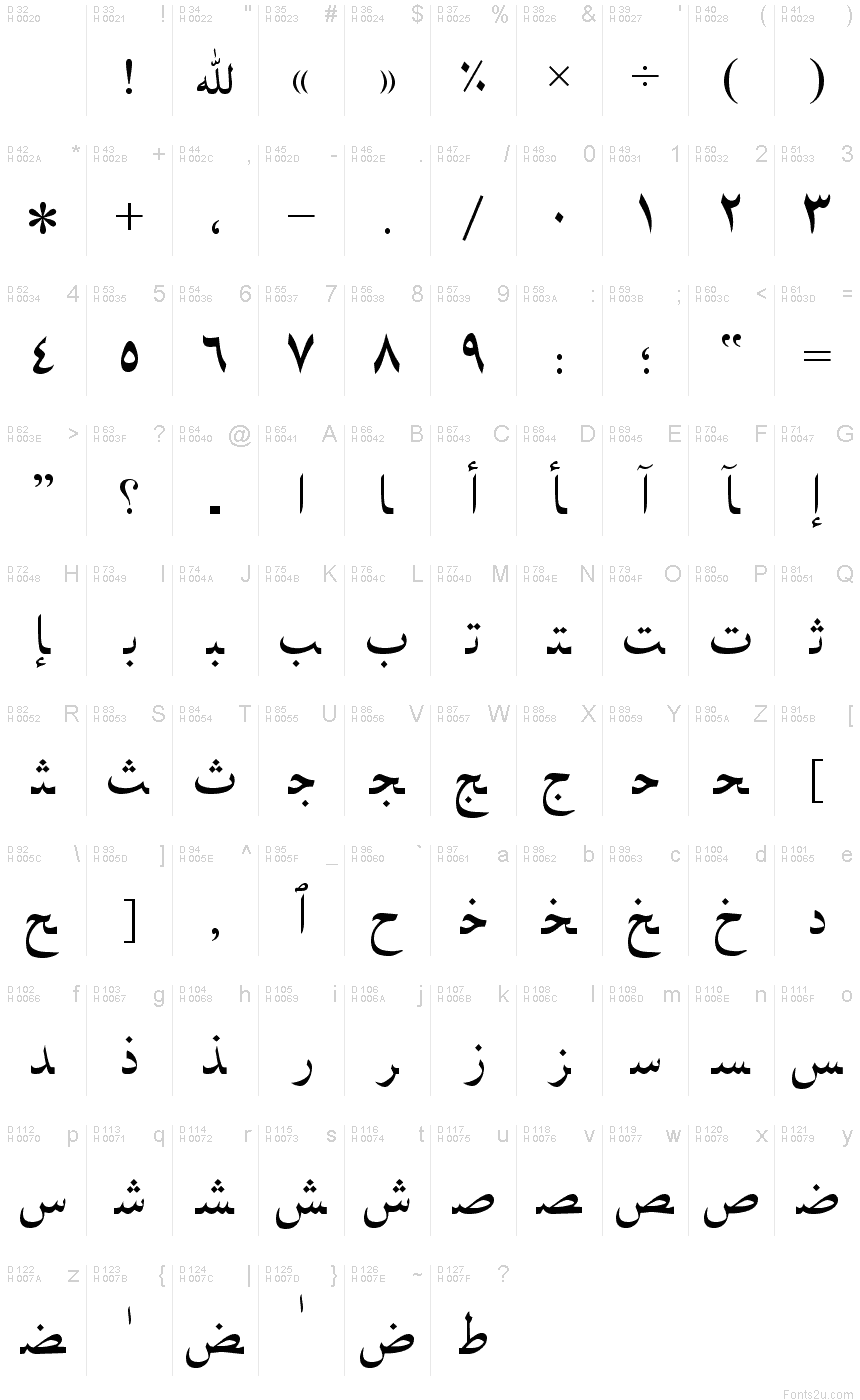
ArabicNaskhSSK
Arabic Naskh SSK, przypisywany Southern Software, to darmowy arabski krój pisma kaligraficznego z szerokimi, połączonymi pociągnięciami i ostro wyciętymi zmianami kierunku. Jego kompaktowe formy liter łączą głębokie łuki, spiczaste połączenia i wyraziste kropki w kształcie rombów, tworząc gęstą sylwetkę o formalnym, odręcznym charakterze.
Romboidalne detale mogą nawiązywać do geometrycznych obramowań i wzorów ornamentalnych na okładkach książek, plakatach imprez kulturalnych oraz opakowaniach w języku arabskim, gdzie liternictwo może stać się częścią dekoracyjnej ramki, zamiast służyć jedynie jako podpis. Okładki książek są jego najbardziej czytelnym i przekonującym otoczeniem.